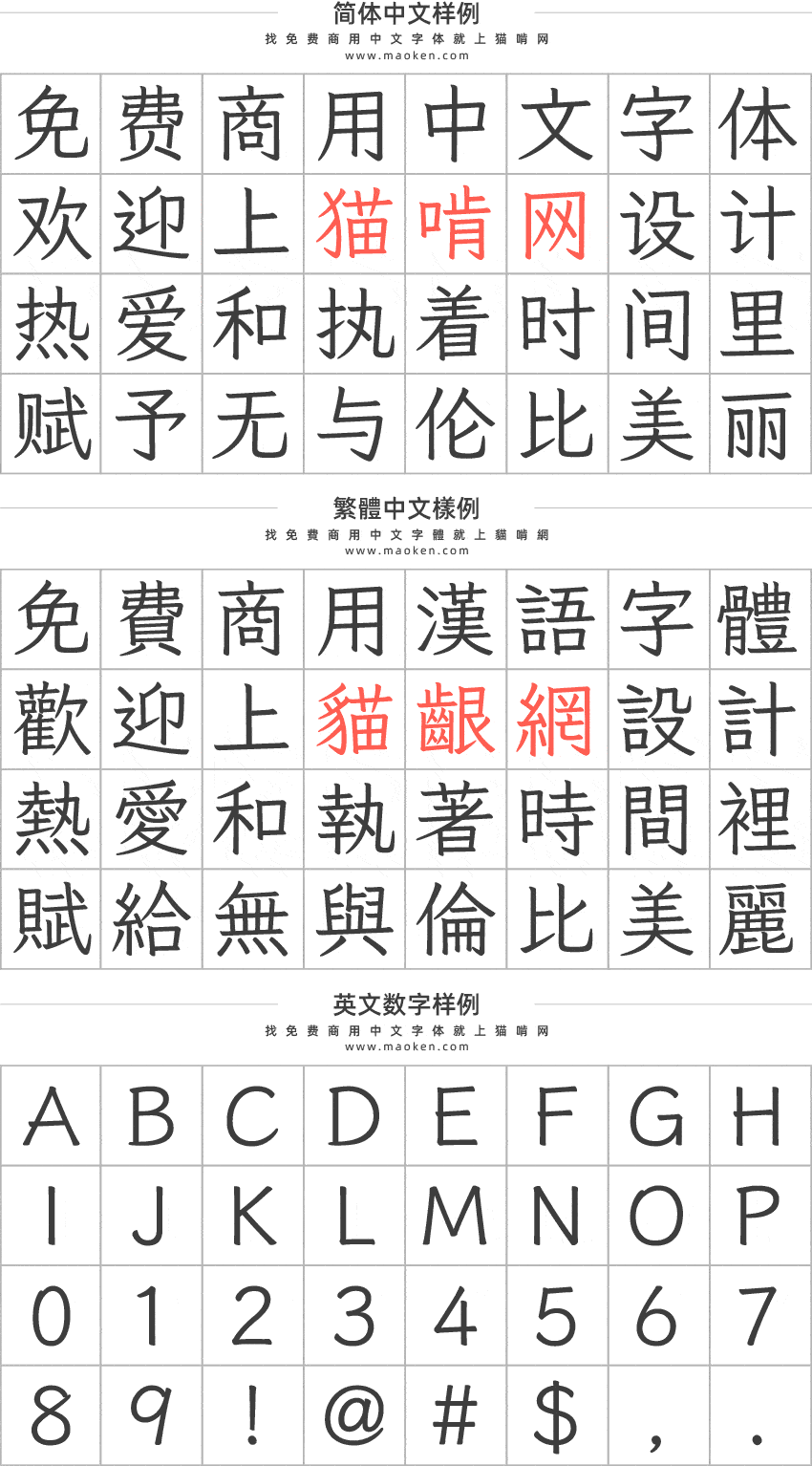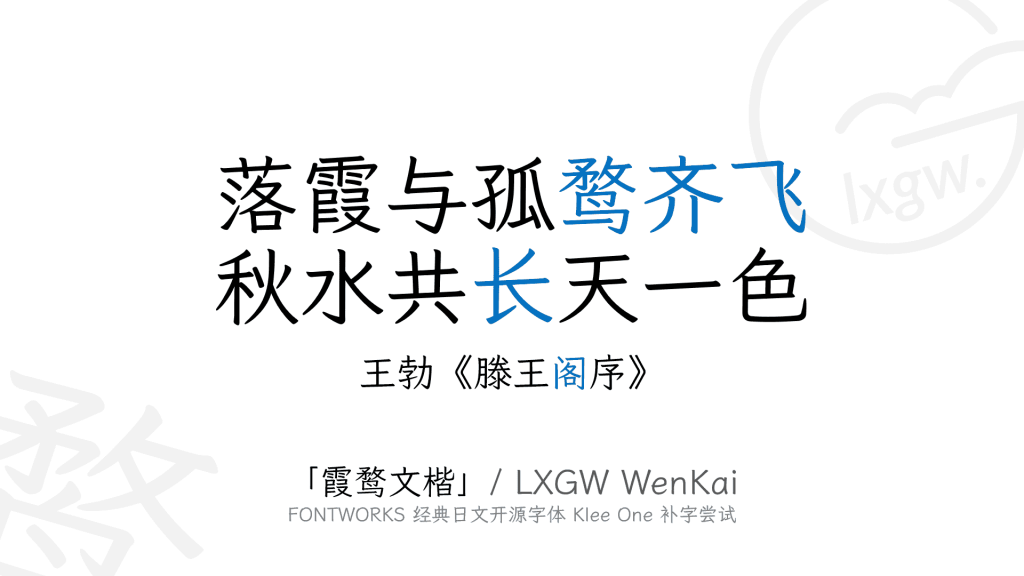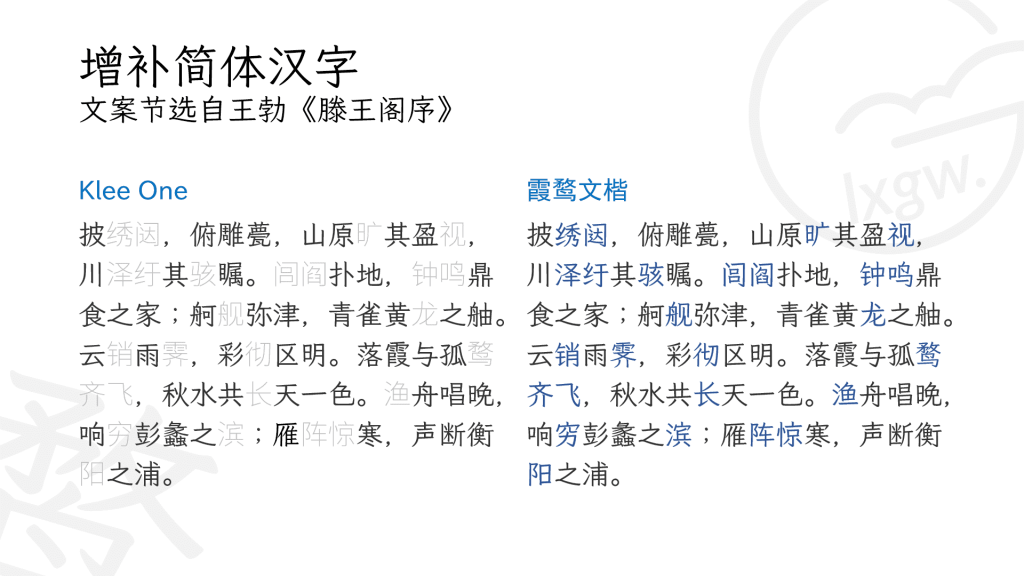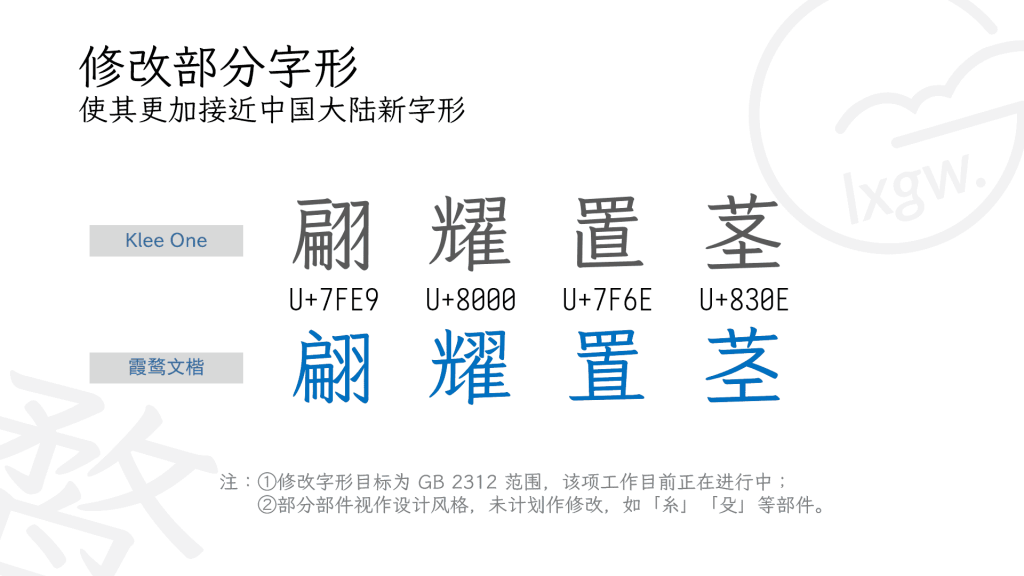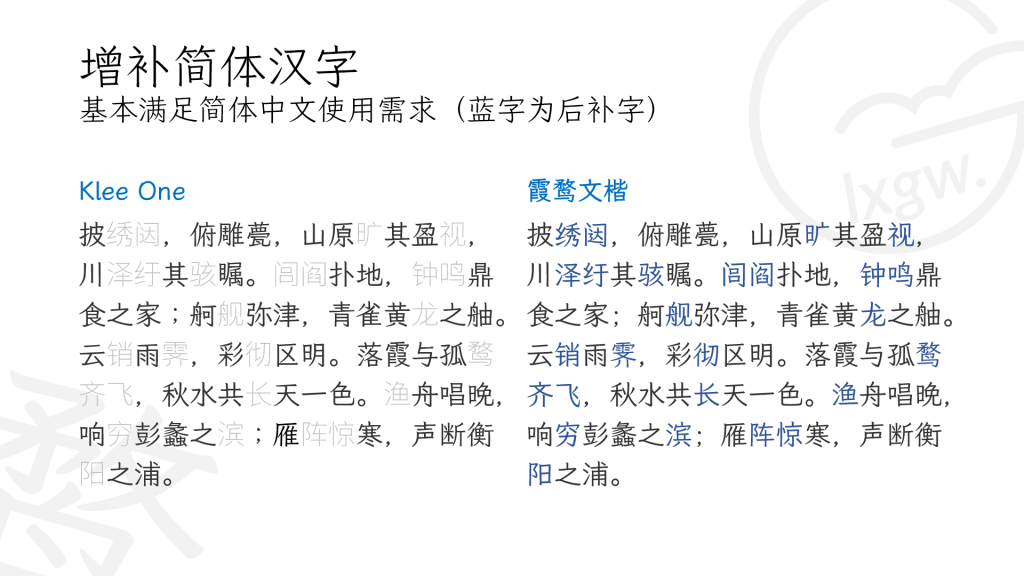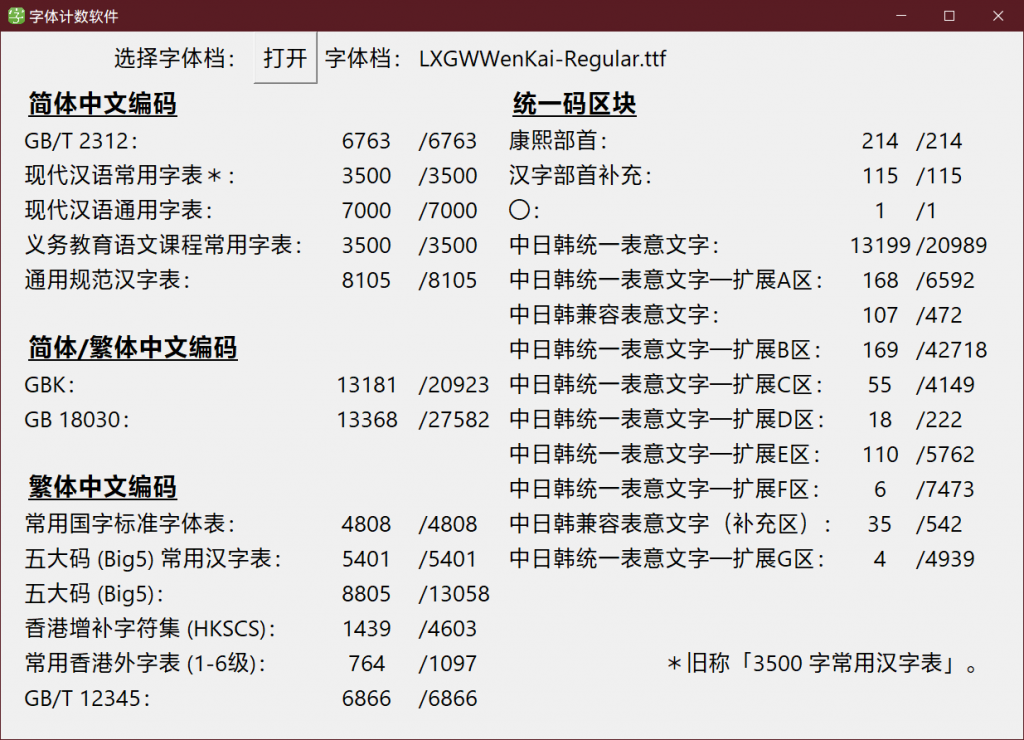
霞鹜文楷:Fontworks开源日文字体Klee One衍生字体
字体作者:落霞孤鹜 (中国大陆) 字体字重:3个
2020 年 12 月,日本著名字体厂商 FONTWORKS 在 GitHub 上发布了 7 款日文字体,分别为 Train、Klee、Stick、Rock-n-Roll、Reggae、Rampart 和 DotGothic16,根据 SIL Open Font License 1.1 授权许可开源。7 款开源日文字体各有各的特点,而这 7 款字体中,字符数量最多的是 Klee。
这是一款有着日本教科书体风格的字体,兼有仿宋和楷体的特点。一些 DIY 字体爱好者曾先后用仿宋等字体补全这款字体,作为手机系统的美化字体移植在 iOS、Android 等手机系统中,受到很多玩机发烧友的欢迎。不过这样补全的字体有一些不足之处。 第一,原有字体和后补字体之间有着一定的差异,致使一些不同的文字(如 Klee 原有汉字与后补简体字)混排之后会有一定的违和感。 第二,由于补字所用的字体为商业版权字体,补全之后不可用于商业用途,还会有侵权的风险。此外,目前现有的开源中文字库里,楷体类寥寥无几,仿宋类则几乎没有。
鉴于此,也为了丰富开源中文字体中的楷体门类,2021 年 1 月 20 日起,本人开始了为 Klee One 这一高质量的日文开源字体补全简繁常用字的尝试。因该字体具有一定的「文艺气息」,命名 「霞鹜文楷」(其实当初是感觉这款字体适合正文阅读定名「文楷」,后来发现这款字体可能并不太适合大段正文排版,相比之下更加适合诗词之类的中等长度文本排版,或者注释排版)。由于 Klee One 字体的 Regular 字重太细不太适合阅读,选取原字体 SemiBold 字重作为 Regular 字重。经过长时间的积累,目前已发展成简繁日韩均支持的 3 字重字体家族 (虽然拙劣粗糙了点) 。
补字计划
简体部分
•  补完原字库所含繁体字对应的简化字;
•  补完简体中文 3603 常用汉字 ①;
•  补完「信息交换用汉字编码字符集(GB 2312-80)」 6763 个汉字;
•  补完「通用规范汉字表」8105 个汉字;
•  修改及优化字形 (范围为 GB 2312 及通用规范汉字表)。目前修改字形的任务已基本完成,但仍有一些字形待优化。
① 包括「现代汉语常用字表」(老 3500 字)及「义务教育语文课程常用字表」(新 3500 字,《通用规范汉字表》一级字表),新老 3500 加一起共 3603 字。
繁体部分
•  补完繁体中文 4808 常用汉字 (台湾地区「常用国字标准字体表」) ;
•  补完「GB/T 12345-90」6866 个汉字;
•  补完 BIG5 一级(常用)汉字 5401 个;
•  补完「通用规范汉字表」内汉字对应的繁体字或港台异体字;
• 补完常用粤语、闽南语、客家语用字。(基于 「常用香港外字表」)
•  常用香港外字表 A-C 级
•  常用香港外字表 1-2 级
•  常用香港外字表 3 级
•  台湾闽客汉字(外字表ㄅ级)
其他
•  补完 CJK 统一汉字基本区 20992 个汉字 (深度学习生成,字形较粗糙) ;
•  补全常用谚文(韩语/朝鲜语)音节 2367 个。
注意事项
3. 由于原版「霞鹜文楷」Regular 字重在 PC 和 Android 屏幕上显示较细,而 Bold 字重需要在粗体模式下才能调用,特制作以 Bold 字重为基础的 霞鹜文楷屏幕阅读版 / LXGW WenKai Screen,加粗后的「霞鹜文楷」与 Windows 默认英文字体 Segoe UI Regular 粗细相当,PC 和 Android 手机屏幕阅读更加舒适,无需特别切换到粗体模式。
4. 另有更粗且经过手工调整的 霞鹜臻楷 / LXGW ZhenKai,加粗的同时减少笔画黏连。目前正处于测试阶段,最终将做完 GB 2312 及《通用规范汉字表》。
5. 为便于开发者将字体嵌入软件中,按照 v1.008 的字库大小提供 霞鹜文楷轻便版 / LXGW WenKai Lite。与 v1.100 版本的霞鹜文楷相比,剔除 v1.100 版本增补的一些较不常用的汉字,回到过往版本的体积。若完整版有字形优化或特性更新,精简版也将会跟进(大量增字除外)。精简版不包含谚文。
7. 对于搭配的西文字体,推荐 Ysabeau 系列字体。另有 Ysabeau Office 与霞鹜文楷轻便版的合并字体 LXGW Bright,采用 字体合并补全工具 将两款字体合并而成,提供 TTF 和 OTF 两种格式。
8. 另,本字体也有供繁体中文用户和旧字形爱好者使用的 繁体中文版,基于轻便版制作,采用旧字形写法,主要采用 Klee One 的隐藏字形,部分部件手动修改 (大部分部件参考一点字坊「传承字形标准化文件」,借助「汉文博士」「国学迷」「字统网」 等工具按部件查字,对字形进行修改)。此外已有基于 Klee One 改造的繁体中文字体 芫荽 / Iansui,采用台湾地区的教育标准字形,有台标字形需求的可使用「芫荽」字体。
• 统一调整以下汉字:㑩㕮㛅㧎㧑㩙㳇㴔䋲䢀䢁䢂䥺䥽专东习买仌仪伡伣伤伪佴傤僿儾军冻凘创劐匦卖卤厍发启呃呋呓呖咡哕哚哧啭啰喼嘧噘噻囔囫围囵圇场坜坠垛堇堑塆头妫媵嫠嬏嬚实屰岘岵岽崭库废心忏恽惭懑懒戗战戹扬报拣拨挕挥掷揙揽搅摊撵擀攤攮敩斩旸晕晖暂暵曌杨枥枧栋栮桌梿棸椝椠榄榉槼殇殸毂氟汤沉沥沩泺泼洱浑浼涟渐渑湢溧滗滚漦灢灭炀炼烫煏煞熯燫爱犛獭玎玚现珲琏畀畅疡瘝皲盯瞒砀砗砚砯硇稳窥窸笃笫笾箅箩篮籜糌緗练绳缃缆罗翘翚翪翸肠胨臁舆苃茇茳茺荡荤荥荪莲萝葦蓝蓦蘀虾蚁蚬蝇螨蟎蠊衅衈衔补衮袯裈裢裤观规视觊觋觞訚譧诨贬贱赂赃赅赈赌赎赔赚赵趖踦踯蹒车轧轨轩轪轫转轭轮软轰轱轲轳轴轵轶轷轸轹轺轻轼载轾轿辀辁辂较辄辅辆辇辈辉辊辋辌辍辎辏辐辑辒输辔辕辖辗辘辙辚进违连选逊逛邓邗郓酦鈀鉺錾鏹鐮鑔鑤钒钖钤铒铴链锹锼镰闪闲闻阵陈陴隐靰韋韱飏饢饧馕駪驴驵驺驽驾骁骂骄骆骇骈骋骏骑骒骖骗骘骚骛骜骝骞骠骡骢髒鬶鬷鬹鮈鰳鲢鳓鳦鴯鵃鵪鸧鸫鸸鹌鹰齉齐龄𠃓𠊟𠺝𡁶𢽾𣱝𥇢𦈃𧝝𨐈𩽼𪠳𪨶𪮶𫂈𫈟𫉁𫏐𫐄𫐐𫐑𫐓𫐖𫐘𫟦𫠣𫵷𬍡𬒗𬟽𬨂𬨎𬳶𬳽𬴂𮝴𮝵𮝷𮝸𮝹𮝺𰅊𰛒𰹰𰹲𰹷𰹹𱇣𱺰
• 单独调整汉字:㻞䴗值囱埴底探暍植殖濂琛碥稙簧綧翩觭(㑈㚂䨮䱁壡愇欜禃菦)
• 修复「䩕U+4A55」误显示为「䭹U+4B79」的问题。
• 重制以下扩展 A 区字形:㐓㒑㒛㒦㓮㓳㓼㔤㔥㕤㕿㖂㖑㖘㖠㖪㖺㖼㗖㘍㘑㙀㙑㙰㙱㙵㙶㛋㛑㛸㛽㜇㜔㜟㜯㜵㜼㝊㝐㝒㝓㝕㝚㝜㝞㝢㝰㝲㞄㞅㞈㞒㞙㞟㞡㞤㞥㞩㞯㞱㟑㟔㟕㠡㠨㡔㢃㢄㢅㢏㢞㢬㢼㣋㣏㤀㤮㤷㤻㥑㥞㥡㥯㥺㥼㦈㦌㦏㦢㦦㧧㧳㧷㧿㨜㨧㨲㩄㩓㩔㩰㩹㫜㫥㫱㫿㬂㬄㬏㬑㬞㬨㬯㭇㭞㭰㭹㮍㮗㮚㮜㮥㮪㮭㯁㯔㯜㯞㯦㯯㯼㱊㱡㱻㱽㲐㲑㲦㲩㳈㳏㳐㳝㳨㳮㳰㳴㳼㴃㴄㴅㴇㴎㴕㴛㴟㴡㴤㴮㴼㵁㵂㵏㵚㵺㶇㶎㶺㷀㷊㷐㷗㷩㷰㷹㷺㸀㸊㸑㸪㸷㸻㹂㹝㹠㹤㹼㺂㺅㺘㺚㺡㺾㻀㻆㻓㻝㻟㻤㻥㻦㻭㻳㼉㼔㼞㼠㼪㼮㼳㼴㽄㽜㽴㽶㽸㽹㽾㽿㾁㾂㾃㾉㾎㾐㾒㾔㾘㾚㾛㾠㾣㾧㾫㾯㾴㾶㾺㿇㿑㿖㿿䀎䀼䁂䁍䁜䁦䁶䁺䃞䃦䃵䆥䆳䆶䆼䇗䇜䇵䈋䈍䈗䈧䈮䈳䉏䉕䉷䉻䊃䊄䊊䊋䊏䊐䊕䊰䋪䋮䋰䋷䌂䌡䌲䌴䍕䍝䎆䎻䏨䐆䐊䐍䐚䐼䐾䑁䑌䑢䑫䑯䑶䑼䑾䒞䒡䒥䒬䒮䒯䒺䓊䓠䔒䔣䔨䕂䕆䕉䕙䕝䕠䕦䖈䖸䖾䗗䗘䗯䗸䘁䘉䘧䘫䘬䘶䘷䘸䙊䙋䙖䙻䙾䚇䚉䚙䚴䚶䚷䚹䚽䛂䛃䛄䛈䛋䛚䛛䛝䛞䛤䛸䛼䜉䜕䝀䝃䞗䞙䞜䞧䞰䟋䟝䠎䠗䠛䠟䠩䠮䠰䠳䠼䡄䡇䡌䡎䡏䡗䡙䡞䡷䡹䡼䢑䢚䢩䢰䢲䢳䢾䣊䣎䣗䣞䣤䣸䣹䣻䣽䤀䤊䤦䤴䤿䥁䥞䥠䥣䥦䥳䥹䦕䦝䦥䦲䧊䧓䧩䧵䧸䧽䨁䨌䨐䨡䩱䩴䪆䪱䫔䫦䫬䫮䫼䫽䬉䬌䬦䬩䬫䬭䬮䬯䬶䬾䭛䭞䭷䭹䮀䮊䮋䮏䮔䮙䮩䮱䯆䯎䯖䯜䯠䯹䯾䰁䰡䰴䰹䱄䱎䱩䱮䱯䱳䱴䱼䲀䲜䲪䲫䲺䳄䳈䳠䳯䳶䳽䴏(目前还剩 1000 字未重制)
• 补全 JIS X 0213 汉字,保留原有日式写法:𠈓𠌫𠍱𠎁𠏹𠑊𠗖𠝏𠠇𠠺𠢹𠥼𠫓𠬝𠵅𠹤𠹭𠽟𡈁𡉕𡉴𡉻𡋗𡋤𡋽𡌛𡍄𡏄𡑭𡑮𡙇𡜆𡝂𡢽𡧃𡱖𡵅𡵢𡵸𡶒𡶜𡶡𡶷𡸳𡸴𡼞𡽶𢅻𢈘𢎭𢡛𢢫𢪸𢭆𢭏𢭐𢮦𢰝𢰤𢷡𣆶𣇃𣇄𣇵𣍲𣏐𣏒𣏓𣏕𣏚𣏟𣏤𣑊𣑋𣑑𣑥𣓤𣕚𣖔𣘸𣘹𣙇𣜌𣜜𣝤𣟧𣟿𣠤𣠽𣱿𣴀𣴎𣵀𣷓𣷹𣷺𣽾𤂖𤄃𤇆𤎼𤘩𤚥𤟱𤢖𤩍𤭖𤭯𤰖𤸎𤹪𤺋𥁊𥄢𥆩𥇍𥇥𥈞𥐮𥒎𥓙𥔎𥖧𥝱𥞩𥞴𥧄𥧔𥫣𥫤𥮲𥱋𥱤𥶡𥸮𥹖𥹢𥹥𥻂𥻘𥻨𥼣𥽜𥿔𥿠𥿻𦀌𦀗𦁠𦃭𦊆𦐂𦙾𦜝𦣪𦨞𦪌𦪷𦫿𦰩𦱳𦹀𦹥𦾔𦿶𦿷𦿸𧃴𧄍𧏛𧑉𧘔𧘕𧘱𧚄𧚓𧜎𧜣𧝒𧦅𧪄𧮳𧮾𧯇𧲸𧸐𨂊𨂻𨉷𨊂𨋳𨏍𨐌𨑕𨕫𨗈𨗉𨛗𨛺𨥆𨥉𨥫𨦈𨦺𨦻𨨞𨨩𨩃𨩱𨪙𨫍𨫝𨫤𨯁𨯯𨴐𨵱𨸟𨸶𨺉𨻫𨼲𨿸𩊠𩊱𩒐𩗏𩛰𩜙𩝐𩣆𩩲𩷛𩸕𩹉𩺊𩻄𩻛𩻩𩿎𪀯𪂂𪃹𪆐𪎌𪐷𪗱𪘂𪚲